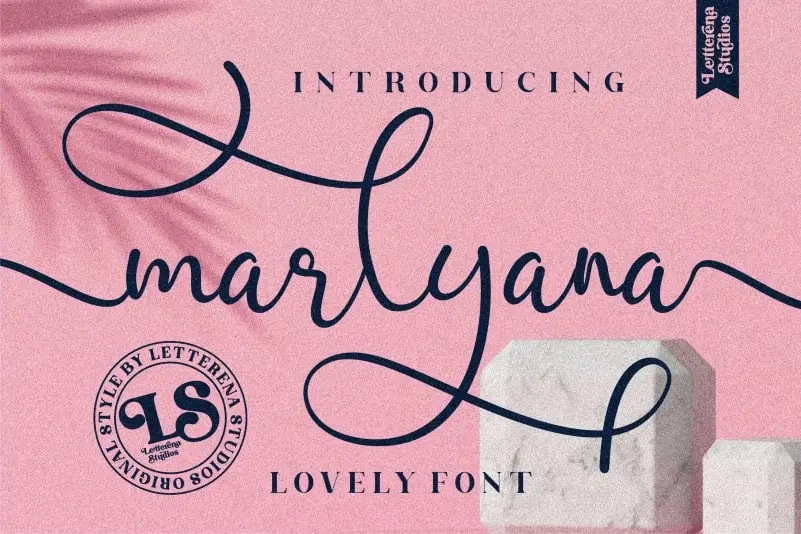
Marlyana Calligraphy Font – Download Grátis
A Marlyana Calligraphy Font é uma escolha perfeita para quem busca personalidade em seus projetos digitais. Escreva cartões de aniversário singelamente atraentes, personalize suas agendas ou adorne qualquer página de conteúdo com sua elegância única e autêntica. Esta fonte é ideal para aquelas iniciativas de arte que exigem um visual especializado, oferecendo uma expressão personalizada perfeita para seus trabalhos digitais. Com seu design refinado, a Marlyana Calligraphy Font adiciona um toque único ao seu trabalho, tornando-o imediatamente mais interessante e memorável. Numa era onde o originalismo é cada vez mais valorizado, essa fonte oferece aos designers uma maneira de expressar suas personalidades e criar arte que seja única e autêntica.